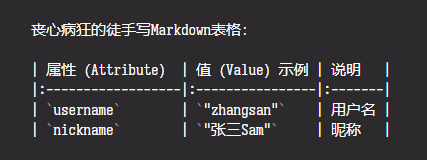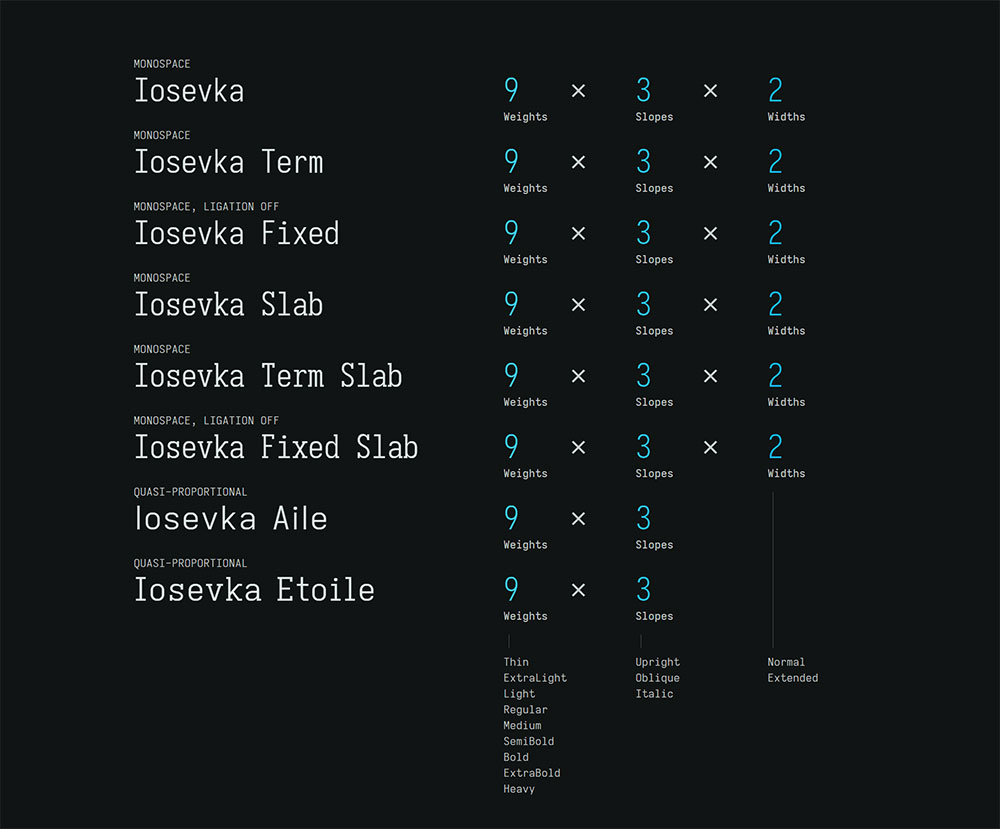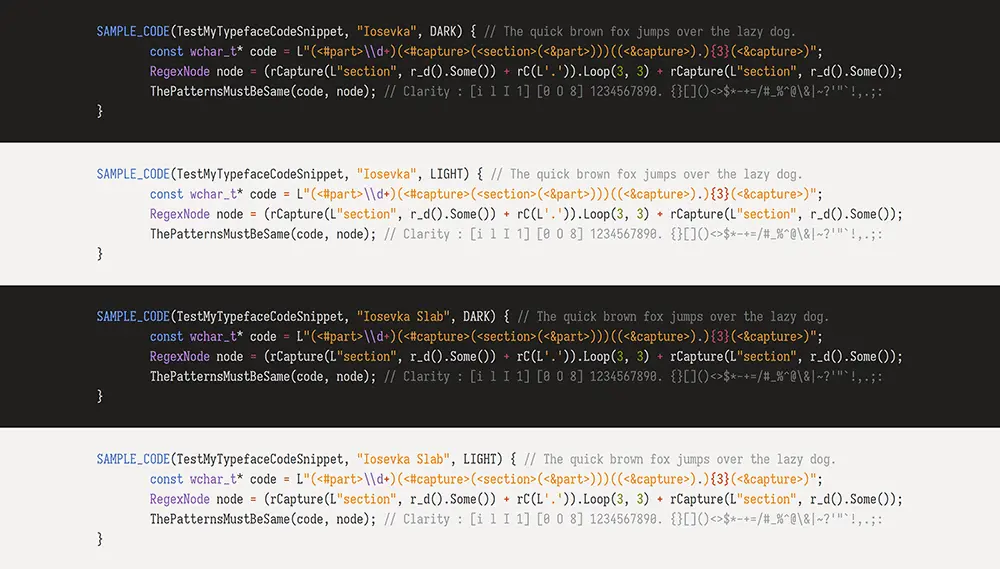
Iosevka。是一款現代化的編程字體集合,除了等寬、oO0 iIl1明顯區分等基本特性外,還有很多非常現代的特性,比如:
多種風格:有非常多的字形可供選擇,襯線/非襯線,多級字重,不同風格的斜體,甚至還有融合了其他常用編程字體設計風格的風味版本。(在其官網上可以動態預覽各種狀態的字形)
字形較窄:採用窄高的風格,水平上可以顯示更多內容。(字體文件中同時包含窄和寬的字形,帶有Extended的就是寬字形)
連體字形:跟JetBrains Mono一樣,對很多常用的字符組合都有連體字形,美觀度直線上升。
嚴格對齊:跟Ubuntu Mono一樣,使用此字體時,中文字符寬度會嚴格等於2個英文字符寬度,強迫症福音。
Iosevka is an open-source, sans-serif + slab-serif, monospace + quasi‑proportional typeface family, designed for writing code, using in terminals, and preparing technical documents.